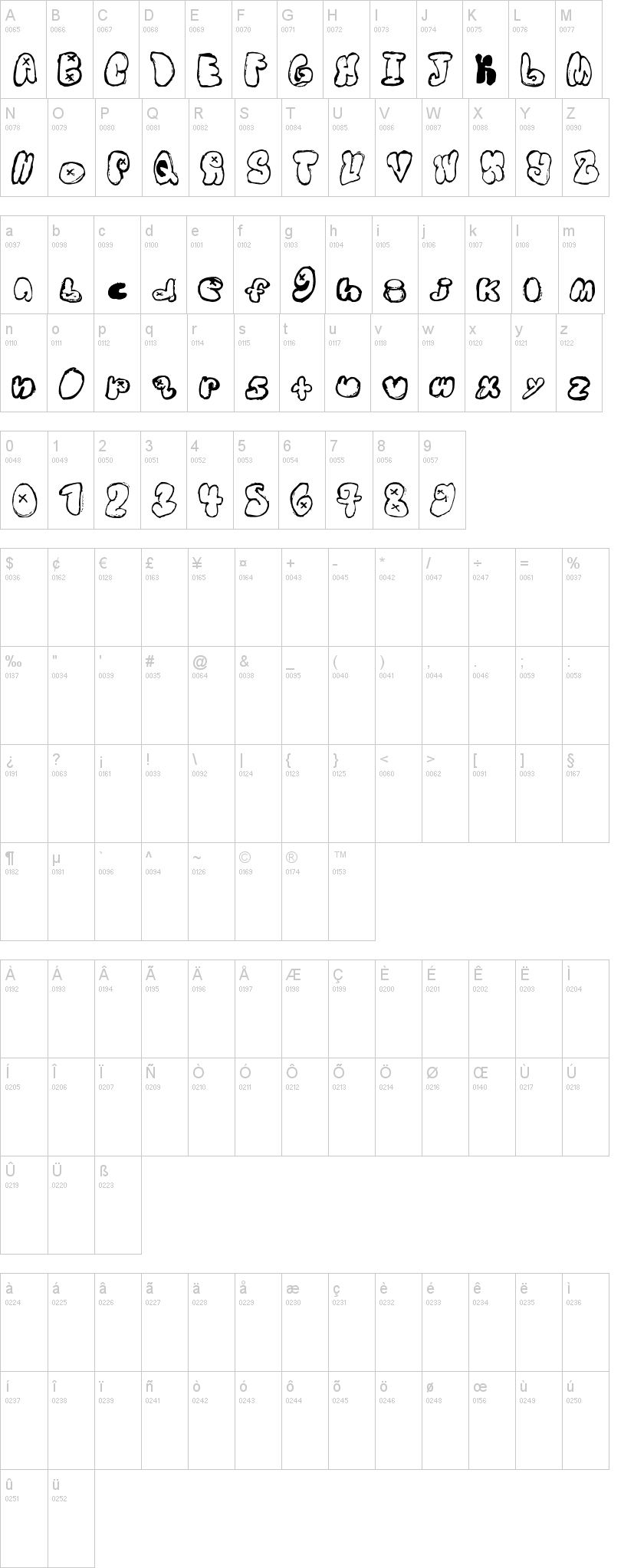
Wyatt Bubbles
Wyatt Bubbles 是一款简约时尚的欧美字体,它拥有灵动的笔画和清晰的轮廓,具有较强的视觉冲击力,可用于创意标志、海报、品牌标识等。它的特点是字母的笔画流畅,线条细腻,给人一种清新、舒适的感觉,比较适合用于清新、时尚的设计中。
Wyatt Bubbles是一款非常不错的手写艺术字体,具有很好的视觉感,适合于文化类的宣传设计、商业类品牌的广告和产品包装设计以及个性化文字排版等较多场景。
Wyatt Bubbles字符映射图